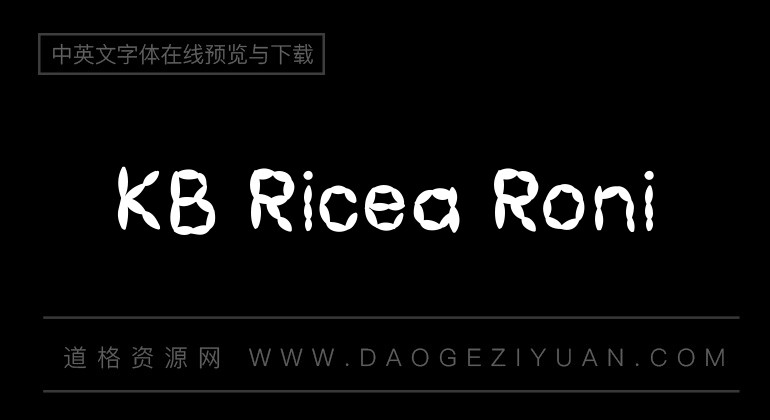
KB Ricea Roni 是一款精美的英文字体,它的特点是简约而不简单,拥有极具特色的细节,它的外观清新淡雅,有着清晰的结构和清晰的轮廓,非常适合用于商业广告、网页设计、印刷制作等。内容介绍
KB Ricea Roni是一款非常不错的手写艺术字体,具有很好的视觉感,适合于文化类的宣传设计、商业类品牌的广告和产品包装设计以及个性化文字排版等较多场景。